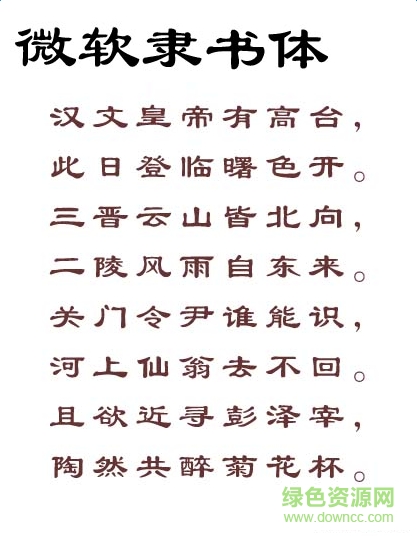
微軟隸書(shū)字體是一款經(jīng)典的隸書(shū)電腦字體,字體簡(jiǎn)潔大方行云流水,可在設(shè)計(jì)創(chuàng)作印刷過(guò)程中使用,一鍵安裝便捷即刻使用非常便捷??靵?lái)綠色資源網(wǎng)下載體驗(yàn)吧!
隸書(shū)字體是漢字中常見(jiàn)的一種莊重的字體,書(shū)寫(xiě)效果略微寬扁,橫畫(huà)長(zhǎng)而直畫(huà)短,呈長(zhǎng)方形狀,講究"蠶頭雁尾"一波三折"隸書(shū)起源于秦朝,由程邈形理而成,在東漢時(shí)期達(dá)到頂峰,書(shū)法界有"漢隸唐楷"之稱(chēng)。
隸書(shū)是由籀文的草率寫(xiě)法演變而成的一種字體。因?yàn)轸ξ膱A轉(zhuǎn)彎曲的筆道太多,寫(xiě)起來(lái)很費(fèi)時(shí)間,所以人們?cè)诜青嵵氐膱?chǎng)合,就將字寫(xiě)得草率一點(diǎn),一些本該工整的弧形筆道變成了比較平直的筆畫(huà)。這種字體在戰(zhàn)國(guó)后期的秦國(guó)開(kāi)始出現(xiàn),后來(lái)逐漸流行開(kāi)來(lái)。
隸書(shū)分秦隸、漢隸和八分。秦隸指秦始皇時(shí)期使用的簡(jiǎn)體字。漢代日常應(yīng)用仍是隸書(shū),但是形體、筆勢(shì)不斷發(fā)展。東漢中期出現(xiàn)莊重典雅的新體,熹平四年(公元175年)以新隸體立石經(jīng)于太學(xué),成為國(guó)家的標(biāo)準(zhǔn)書(shū)體。魏以后稱(chēng)為八分。